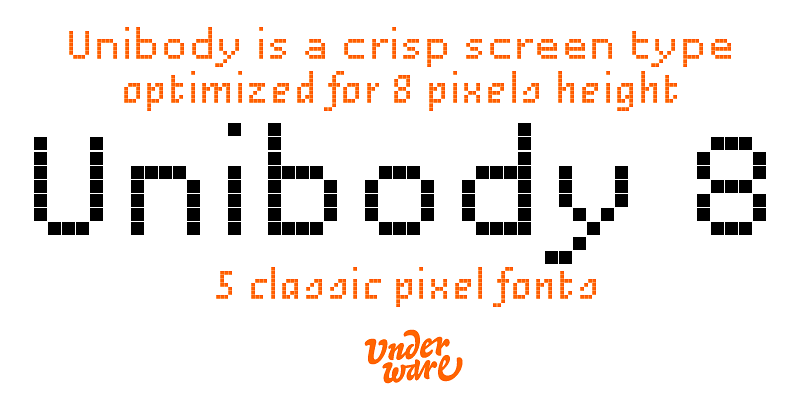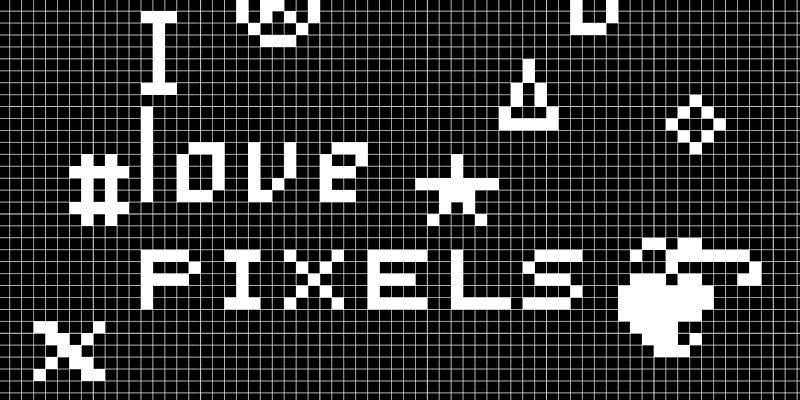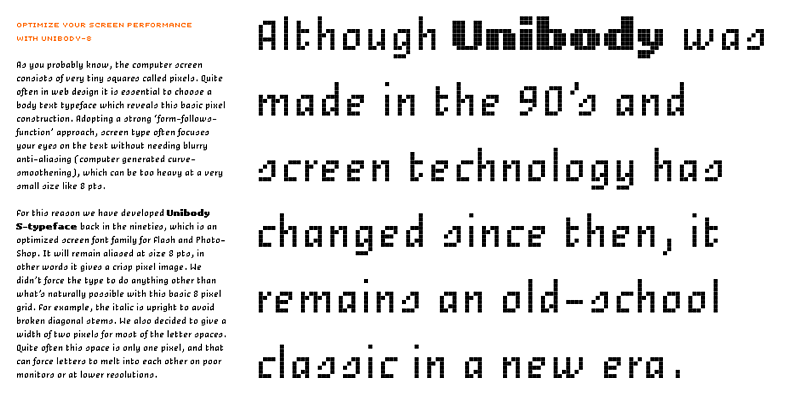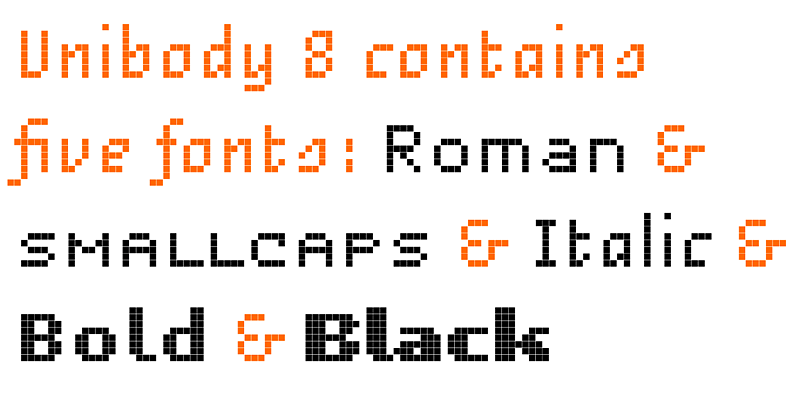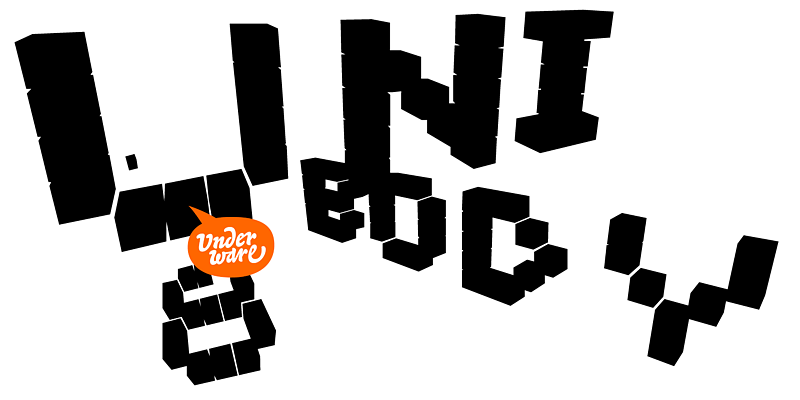
Unibody ist eine gestochen scharfe Bildschirmschrift, die an klassische Pixelfonts aus der frühen digitalen Ära erinnert. Diese Familie mit echter Kursivschrift ist für eine Höhe von 8 Pixeln konzipiert, die jetzt an die aktuellen Technologien angepasst wurde.